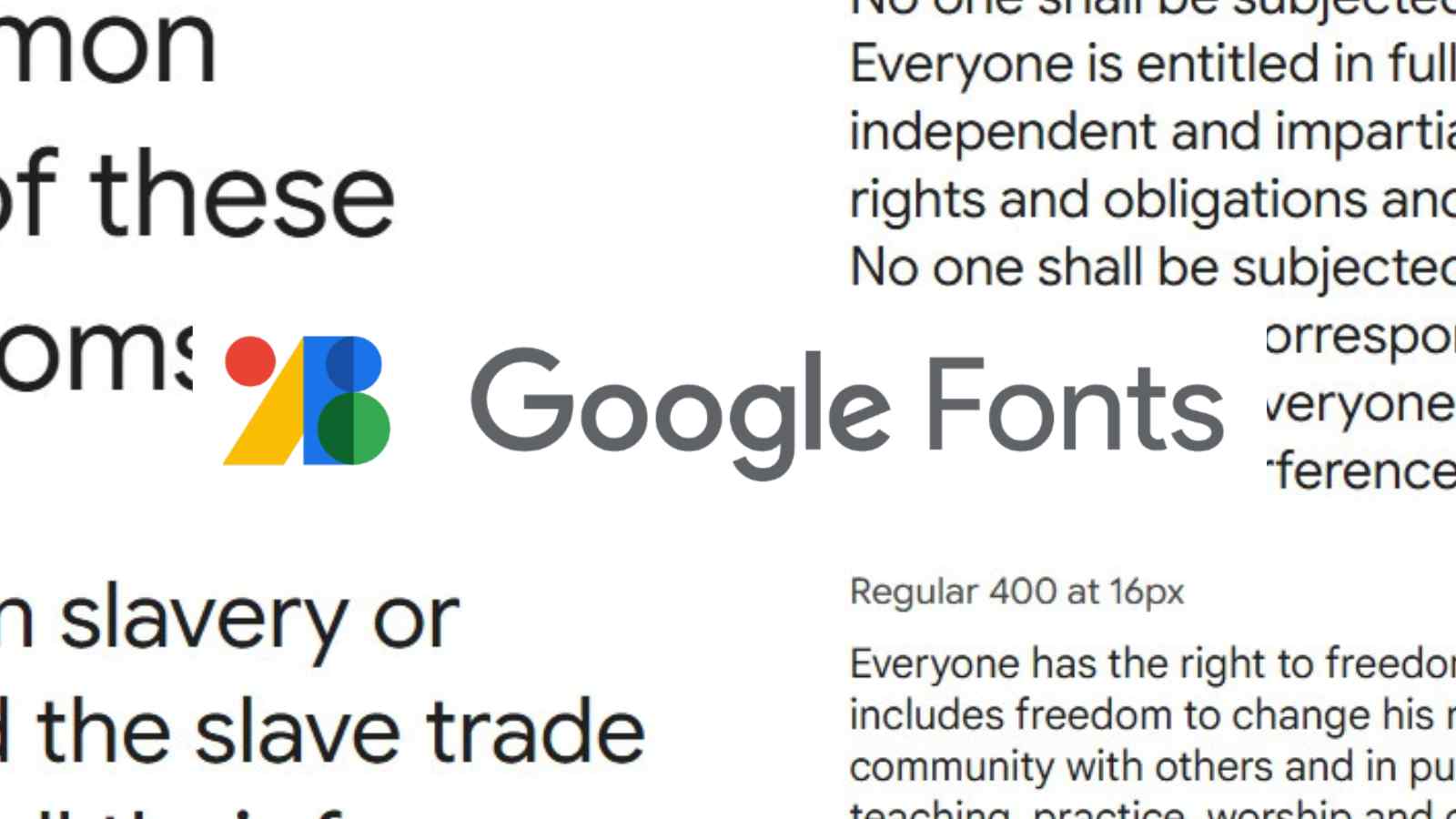
Avevamo davvero bisogno di un nuovo font? La risposta più onesta è probabilmente no, ma questo non significa che l’arrivo di Google Sans nel suo “pacchetto completo” sia una notizia irrilevante. Anzi. Quando un carattere tipografico è così riconoscibile, così legato a un ecosistema che usiamo ogni giorno, finisce inevitabilmente per diventare uno strumento in più, qualcosa che prima non c’era e che ora può tornare comodo in molte più situazioni di quanto si pensi. Google Sans, Google Sans Flex e Google Sans Code non sono semplicemente tre varianti dello stesso progetto, ma tre risposte diverse a esigenze concrete, ora finalmente accessibili a chiunque grazie alla scelta di Google di consentirne il libero utilizzo.
Google Sans diventa pubblico
Google Sans nasce come evoluzione diretta del Product Sans, il font che accompagnò il restyling del logo di Google nel 2015 e che contribuì a fissare quell’idea di semplicità amichevole diventata ormai parte dell’immaginario collettivo. Negli anni, quel carattere è rimasto confinato all’uso interno, diventando una sorta di firma silenziosa delle app e dei servizi del gruppo. Con Google Sans Flex, però, il progetto tipografico fa un passo in avanti deciso: entra in gioco la variabilità, quindi la possibilità di modulare peso, larghezza, inclinazione e spaziature in modo molto più fine, adattando il font a contesti grafici diversi senza perdere coerenza visiva. È un approccio moderno, pensato per chi lavora con layout dinamici, interfacce e contenuti che devono respirare su schermi e supporti differenti.
Poi c’è Google Sans Code, che guarda apertamente al mondo della programmazione. Qui la priorità non è tanto l’identità visiva quanto la leggibilità del codice, la distinzione chiara tra i caratteri, la riduzione degli errori di interpretazione quando si passa ore davanti a un editor. Anche in questo caso si riconosce subito la mano di Google: pulizia, ordine, niente fronzoli, tutto al servizio della chiarezza.
Da firma interna a strumento per tutti
La decisione di rendere questi font liberamente utilizzabili, annunciata ufficialmente già a dicembre, sembra andare oltre una semplice concessione. Da un lato c’è la volontà di creare una maggiore continuità estetica tra le app Google e quelle sviluppate da terze parti, dall’altro emerge l’intenzione di portare questa identità anche negli strumenti di produttività quotidiana. Oggi Google Sans è utilizzabile senza difficoltà in Documenti, Fogli e Presentazioni, diventando di fatto una nuova opzione “di default” per chi lavora nell’ecosistema Google.
Il risultato è un font che punta tutto su chiarezza e leggibilità, con spaziature generose e un equilibrio visivo che non stanca. Non rivoluziona il modo di scrivere o progettare, ma offre un’opzione solida e affidabile, perfettamente in linea con lo stile Google. Ed è proprio questa normalità, così curata e misurata, a renderlo interessante ora che è finalmente alla portata di tutti.